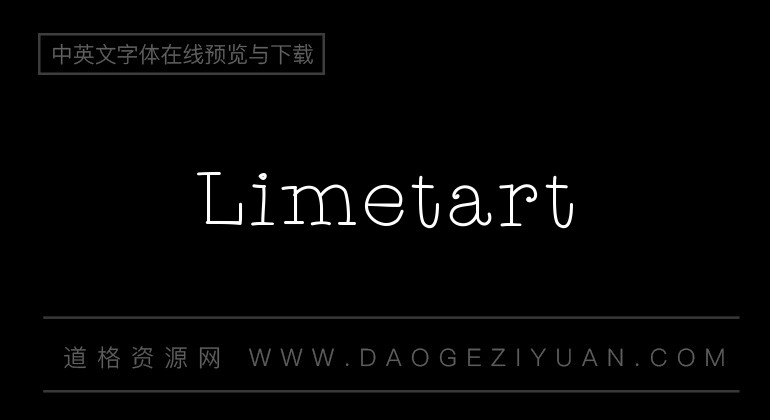
Limetart 字体是一款由字体设计师梁石磊设计的字体,它有着简洁、清新的外观,适合用于排版、logo设计等。Limetart 字体采用了现代技术,使用了更多的笔画,使字体看起来更加清晰,整体外观也更加精致。它拥有多种字重,可以满足不同场景的需求,而且还支持多种语言,可以满足不同国家和地区的需求。内容介绍
Limetart是一款非常不错的手写艺术字体,具有很好的视觉感,适合于文化类的宣传设计、商业类品牌的广告和产品包装设计以及个性化文字排版等较多场景。